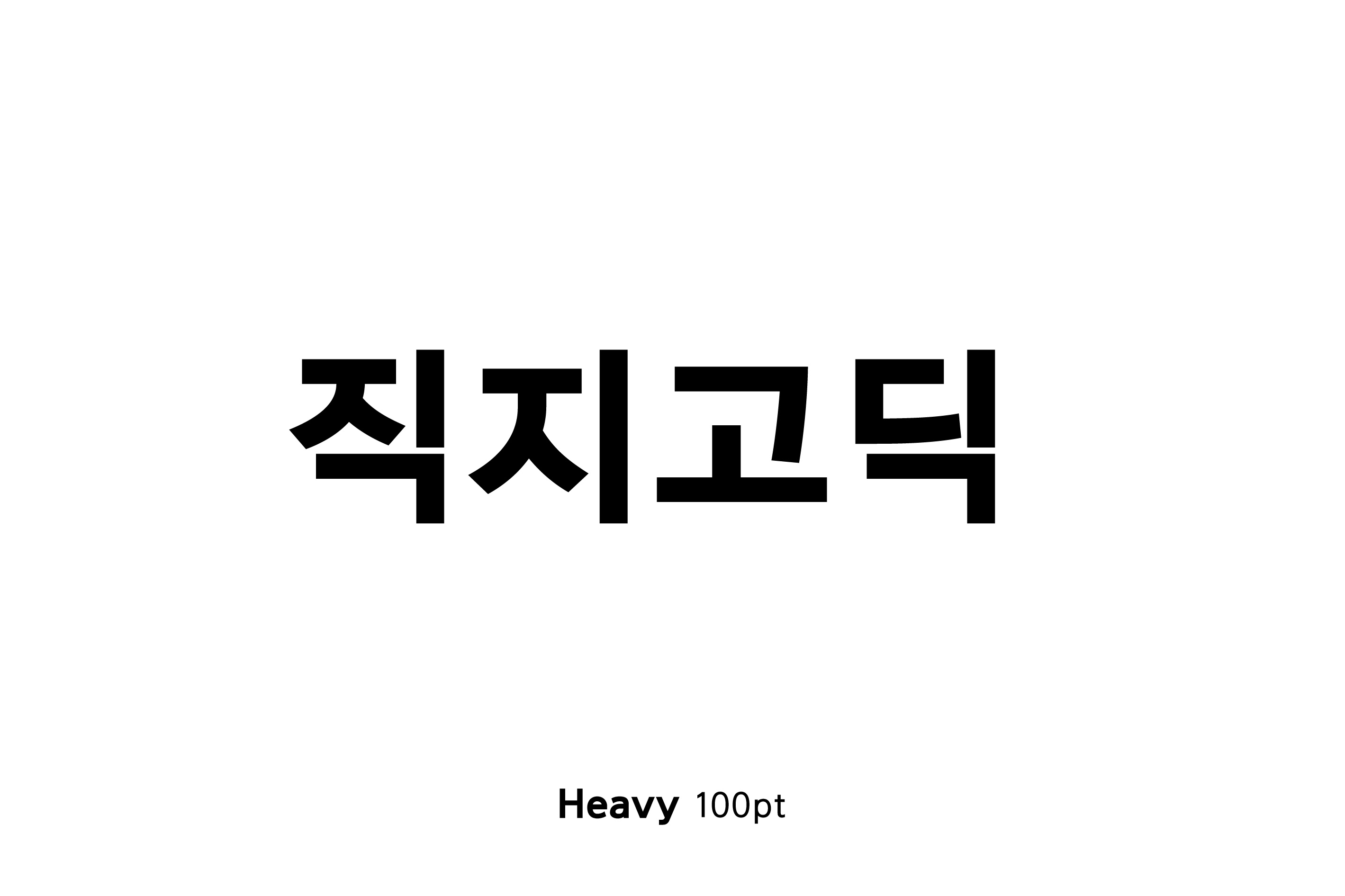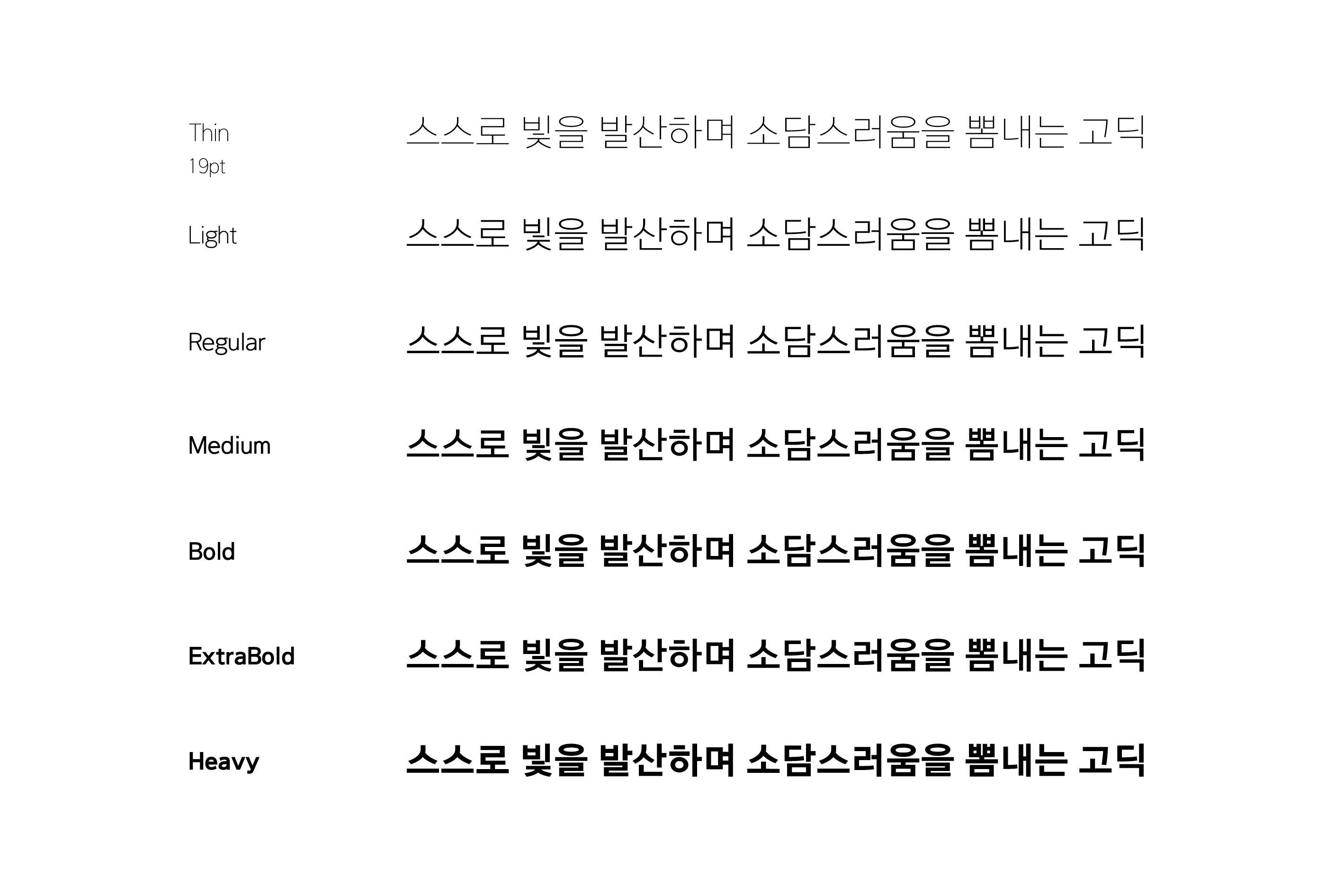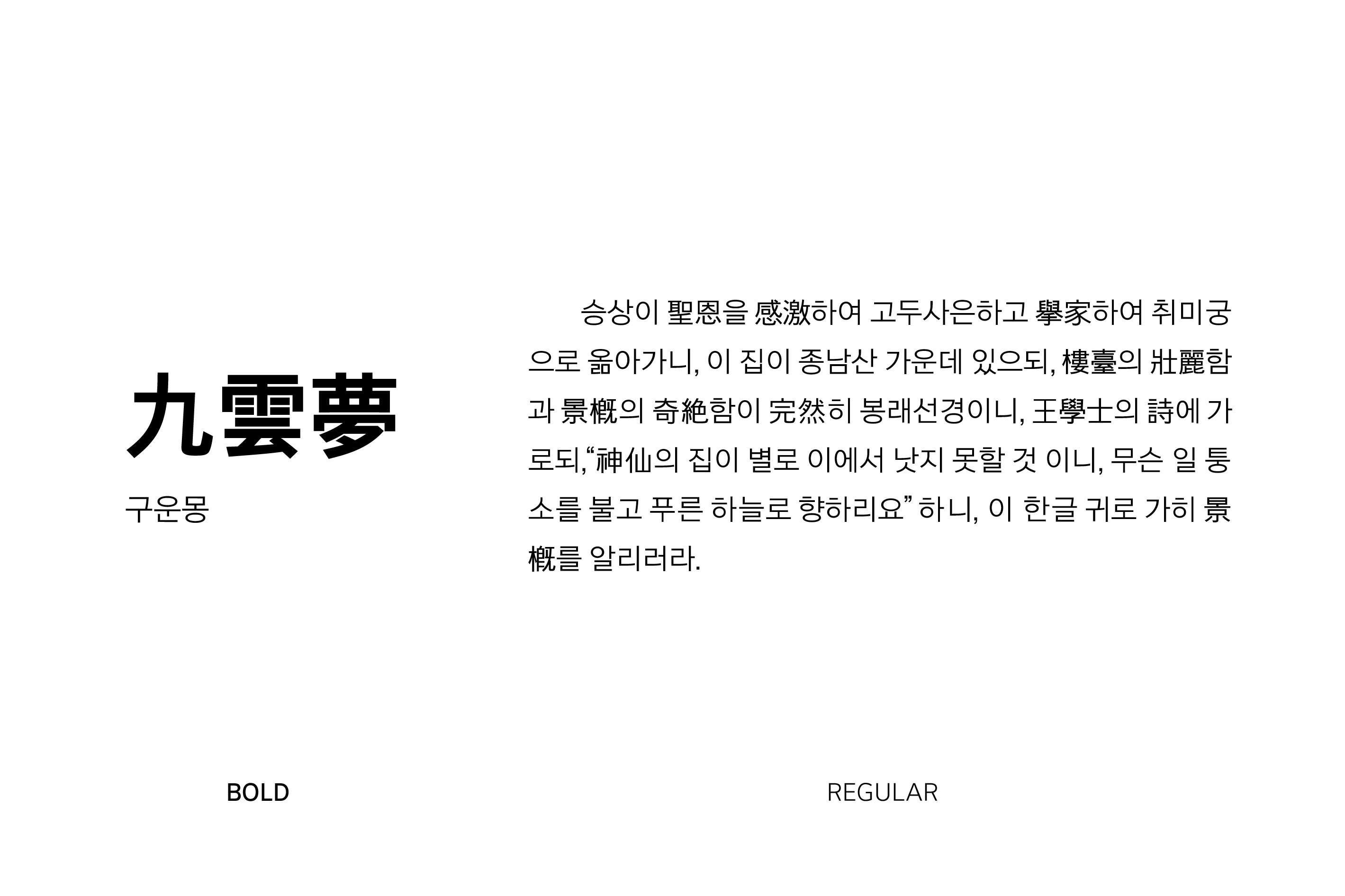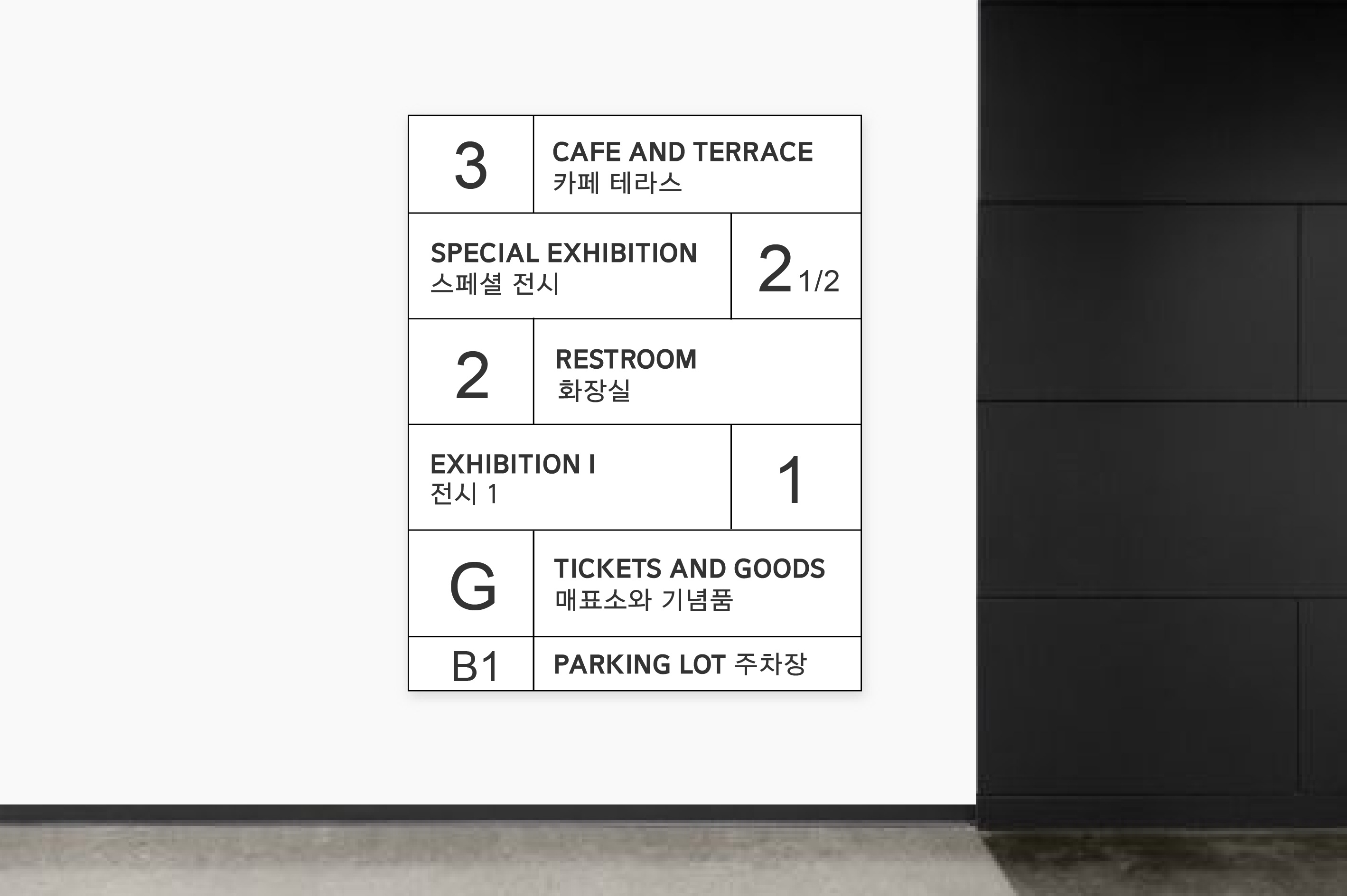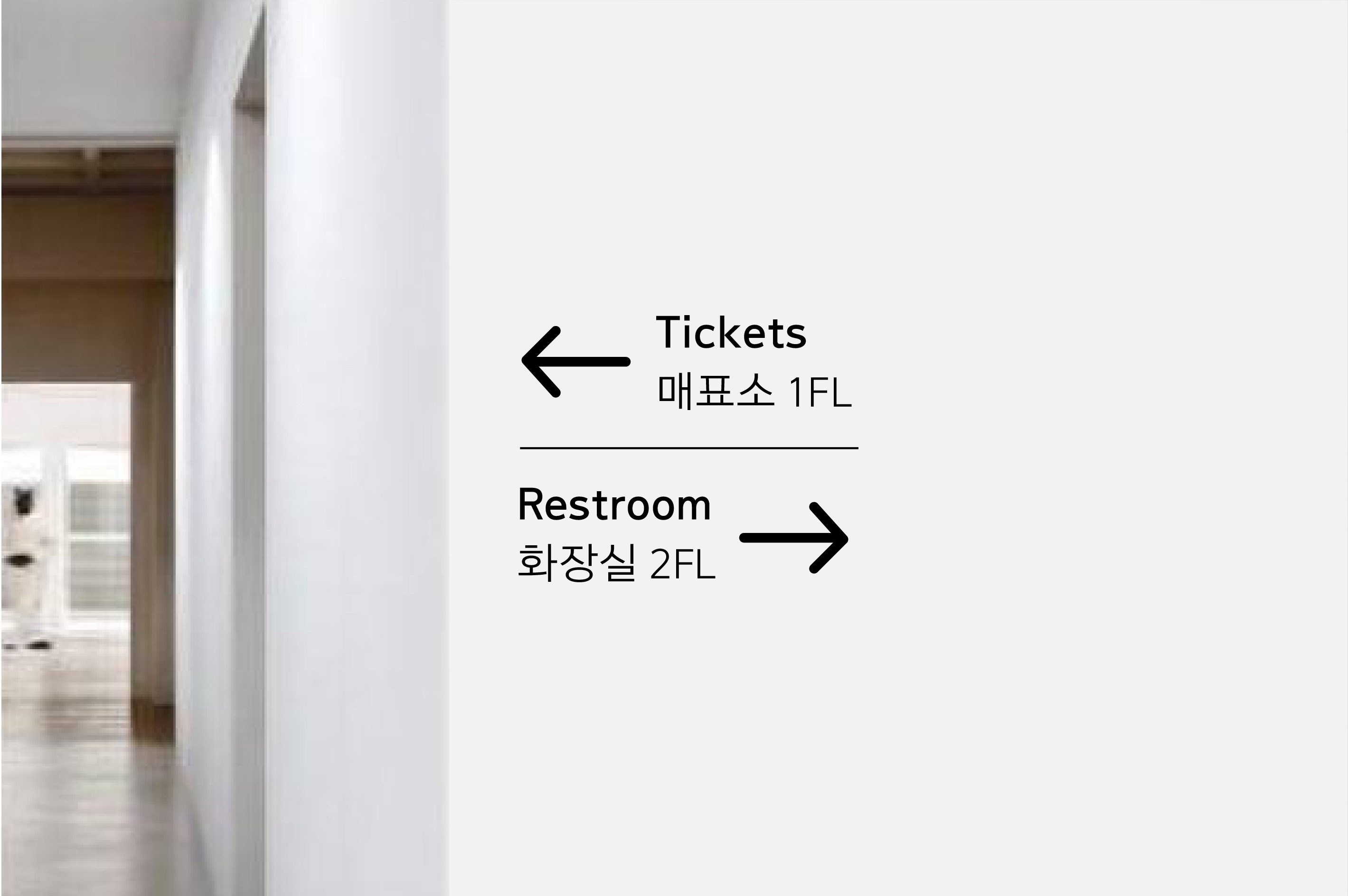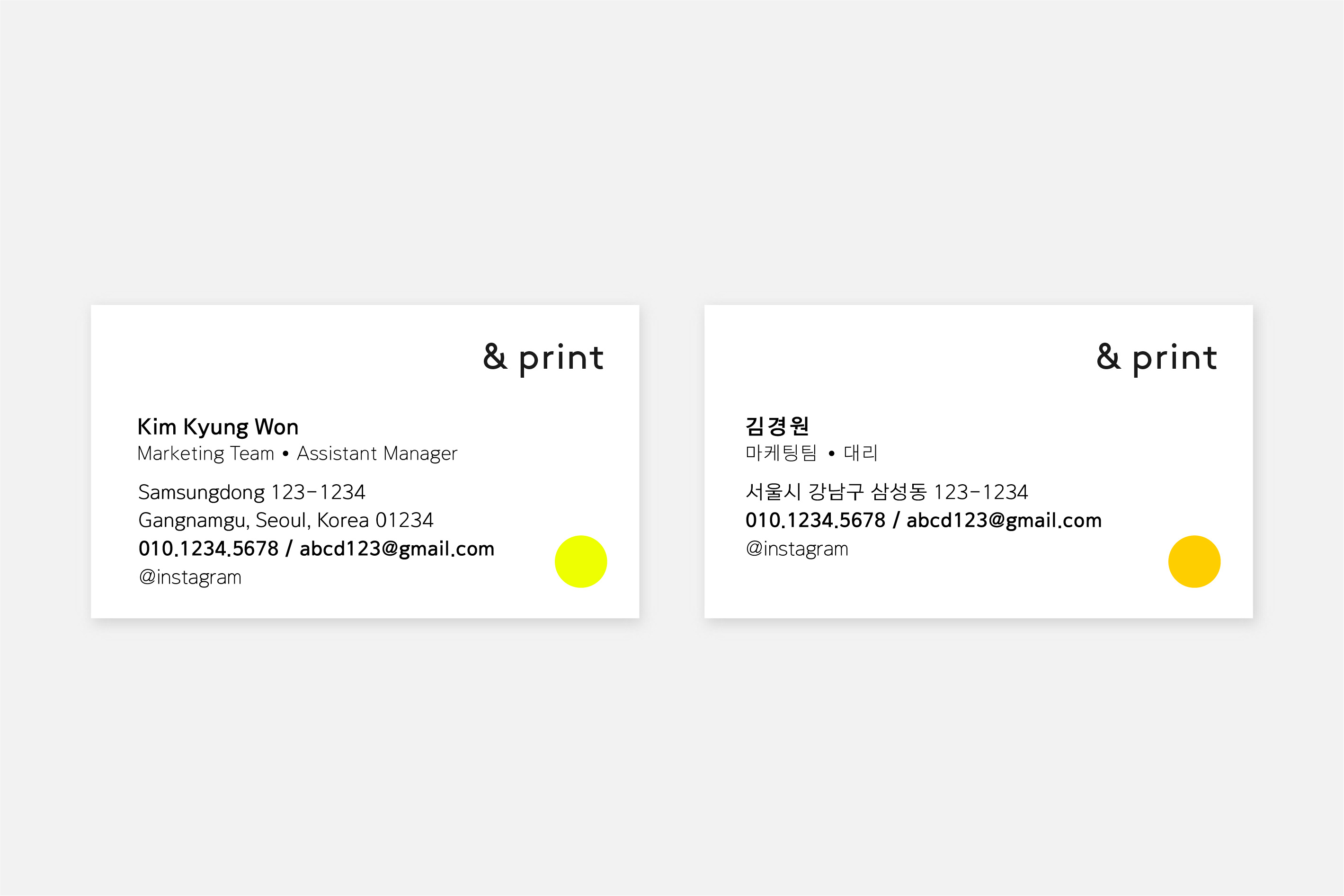
J직지고딕
• 스스로 빛을 발산하며 소담스러움을 뽐내는 고딕
대중적으로 선호도가 높으며 트렌드와 상관없이 꾸준히 사랑받는 서체 시리즈. 높은 디자인 완성도와 가독성으로 심미성과 기능성 모두 만족시키는 서체이다.
직지고딕은 본문용 고딕서체를 사용하는 사용자의 다양한 환경을 분석하여 최적의 자간과 공간 배분을 통하여 심미성과 기능성을 극대화하는데 중점을 둔 서체입니다. 본문용 서체에서 가장 중요한 친숙함과 가독성을 우선으로 염두에 두고 ㅅ,ㅆ,ㅈ,ㅉ,ㅊ 에서 내리는 획의 형태는 일반적인 표현법인 좌우 대칭형의 형태가 아닌 비대칭 형태로 차별성을 두었습니다. 총 7종 (씬-라이드-레귤러-미디움-볼드-엑스트라볼드-헤비)의 다양한 웨이트 구성으로 전문적인 편집 디자이너들과 그래픽 디자이너들의 선택의 폭을 넓혀 까다로운 요구에 부응하고자 했으며 전문가 뿐만 아니라 입문자들 그리고 비전문가인 많은 사람들도 조판하고 사용하기 쉽도록 품질과 편의성을 높였습니다.